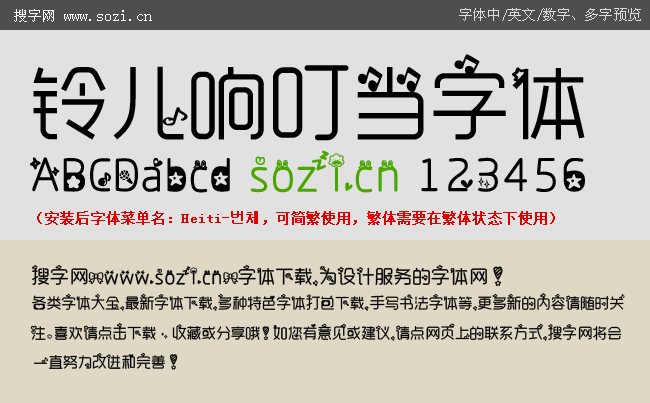
鈴兒響叮當(dāng)字體
搜字網(wǎng)給大家提供一款很有趣的手機(jī)中文字體下載。字體名字叫鈴兒響叮當(dāng)字體,這款手機(jī)字體是以造字工房悅黑體字體為原形,為字體插入了卡通圖案。即保持了悅黑體易識(shí)別的風(fēng)格,又增強(qiáng)了趣味性,特別適合喜歡手機(jī)字體個(gè)性一些的朋友在手機(jī)上安裝使用。